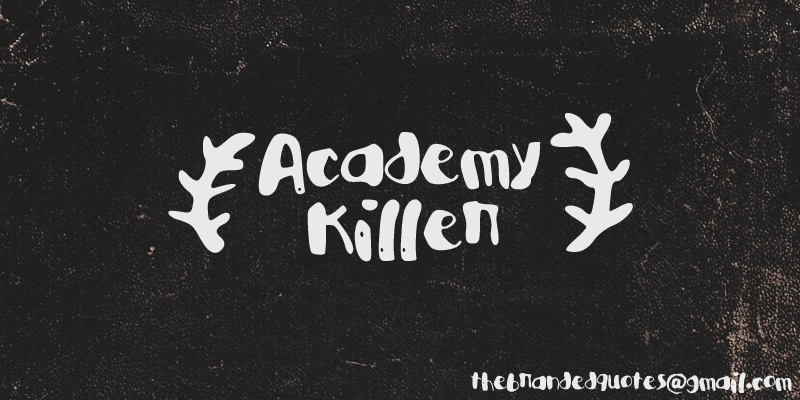
Academy Killer font
A Academia Killer é uma fonte script que oferece uma experiência visual confortável para textos legíveis e elegantes, ideal para projetos visuais criativos. Desenvolvida pelo designer Hamilton, essa fonte combina elementos delicados e fluidos de forma arrojada, tornando-a a escolha perfeita para aplicações variadas como design editorial, anúncios, cartões de visita ou até mesmo ilustrações digitais. Com seu estilo suave e fácil de ler, a Academia Killer é uma fonte versátil que se destaca por sua capacidade de transmitir sutileza em mensagens mais formais, enquanto também enriquece um visual mais descontraído com seus detalhes acentuados. Seja para projetos digitais ou impressos, essa fonte atinge perfeitamente o equilíbrio entre sofisticação e praticidade. Para quem busca uma fonte que combine elegância com facilidade de uso, a Academia Killer é uma excelente escolha. Suas linhas finas e curvas leves garantem um design clean, enquanto seus detalhes sutis adicionarão um toque personalizado aos textos que você criar.